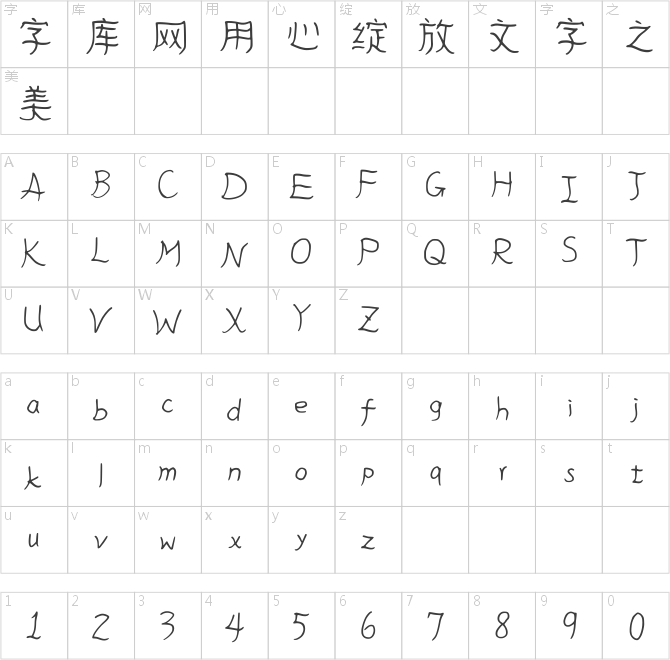
清松手寫體7 詳情頁
字體名稱: 清松手寫體7
清松手寫體7
清松手寫體7介紹
“清松手寫體7”作為游清松先生傾力打造的第七款免費可商用字體系列作品,延續了該系列一貫的人性化與自然書寫特色。這款字體在2024年初次亮相,標志著清松手寫體家族的又一次重大突破與迭代升級。
“清松手寫體7”以獨特的原子筆質感為基礎,融入了更多現代審美趨勢,字形結構更加豐富多樣且不失和諧統一。設計師游清松深入研究漢字書寫美學,通過細膩的筆畫勾勒與微妙的轉折變化,使得每一個字符都仿佛躍然紙上,充滿了生命力和溫度。